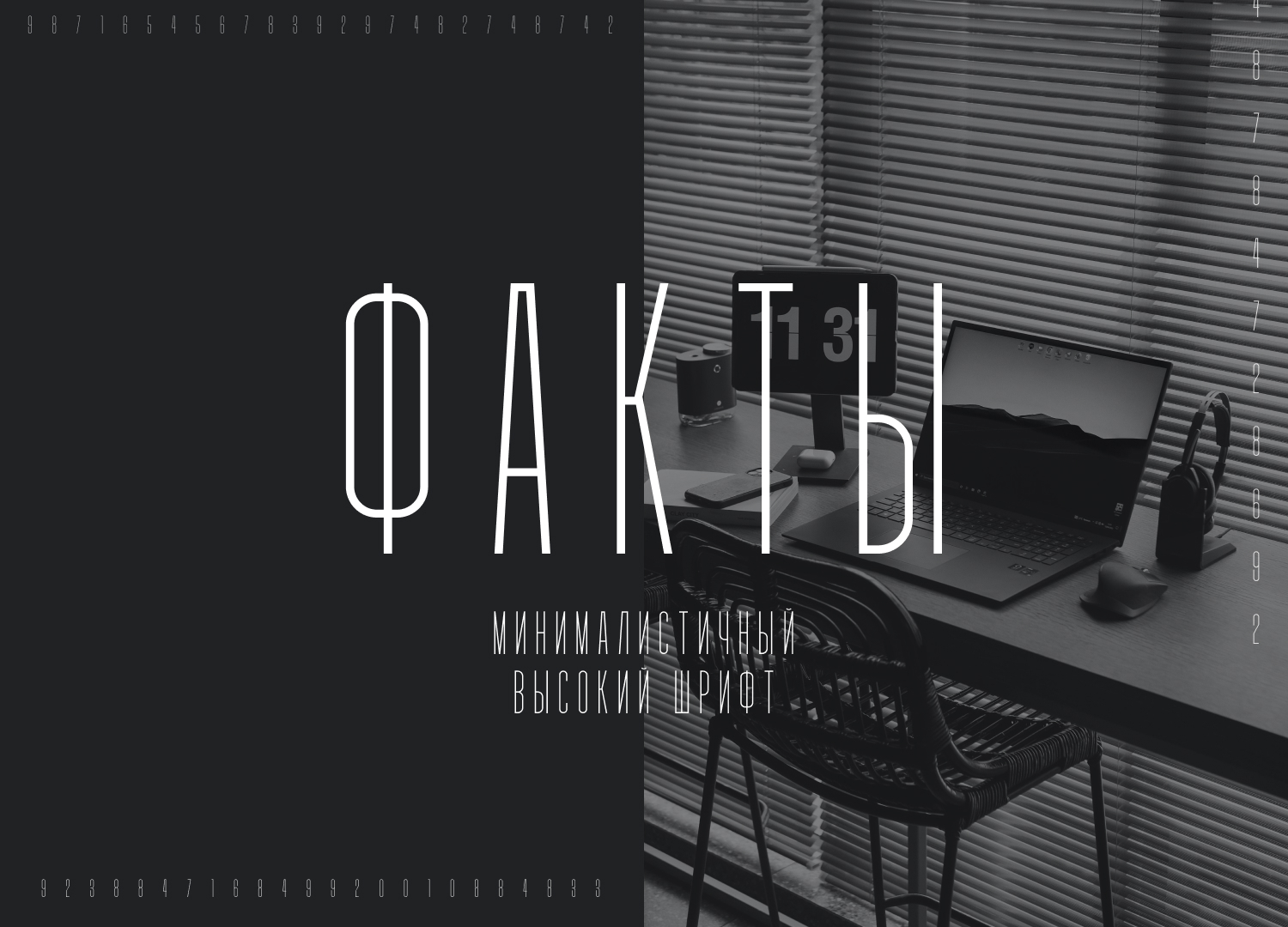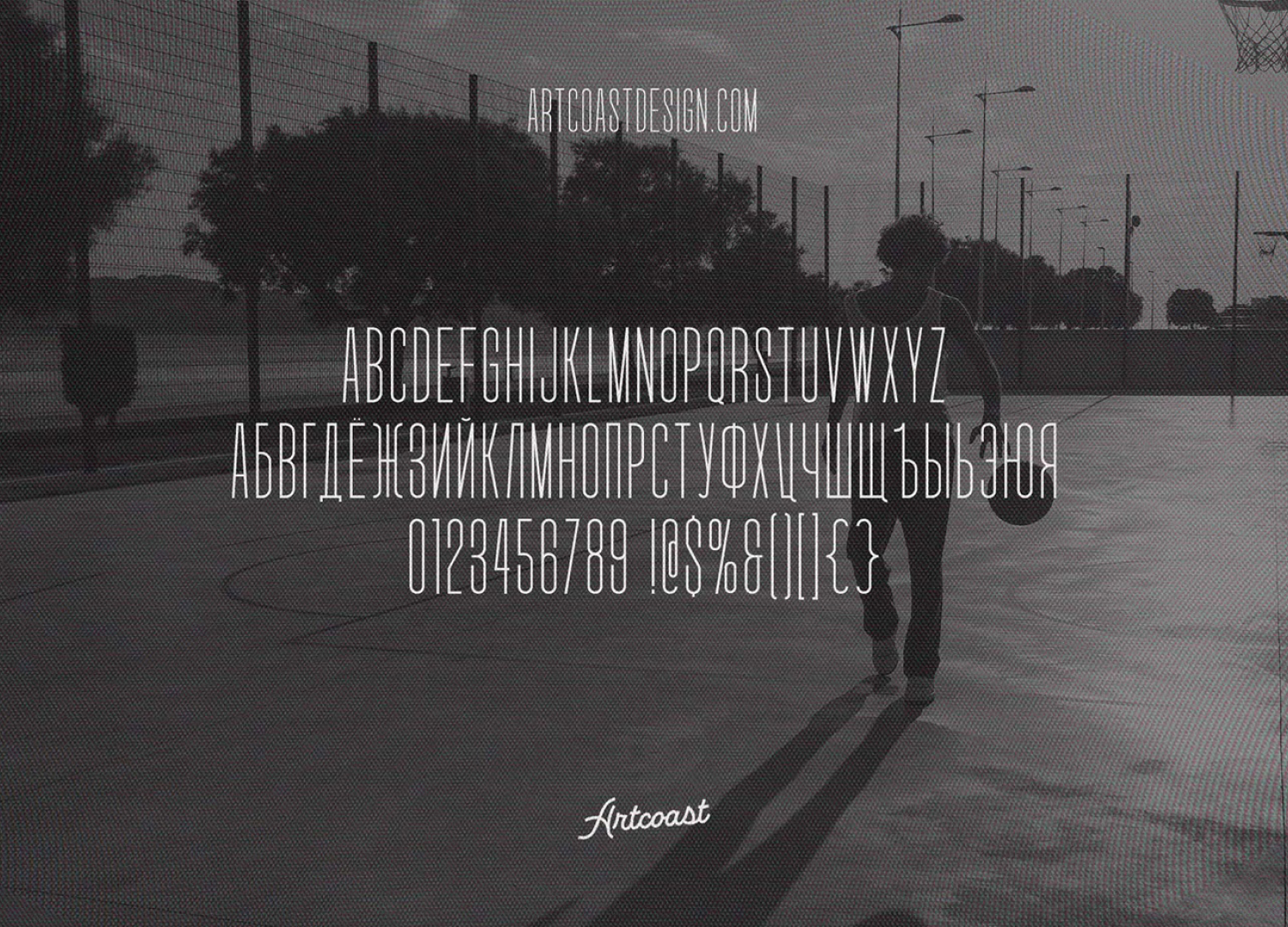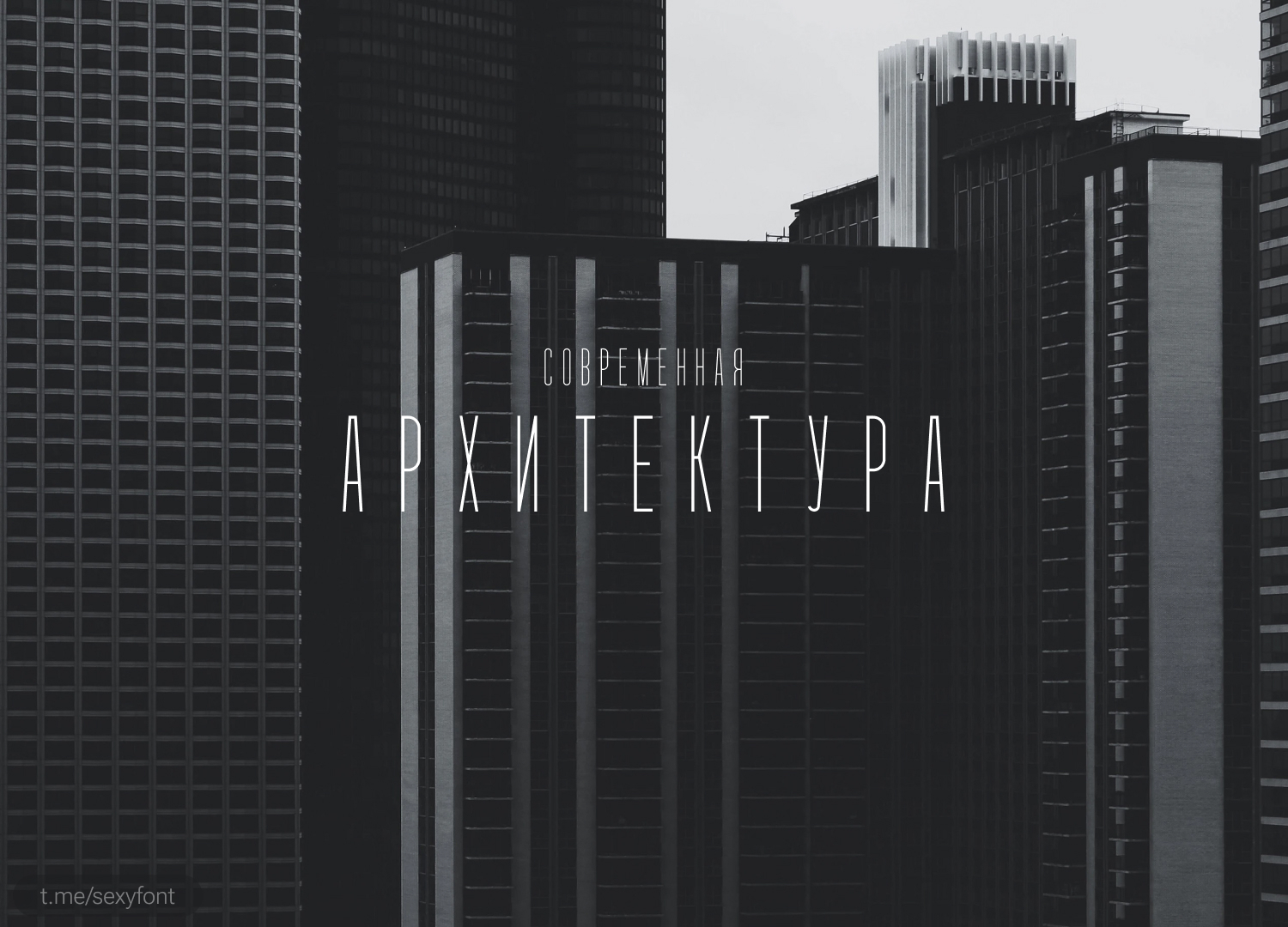
Высокий шрифт SA Vredina
SA Vredina. Высоченный шрифт для твоих проектов. Естественно с поддержкой кириллицы. Других не держим )
Автор: Artcoast Studio